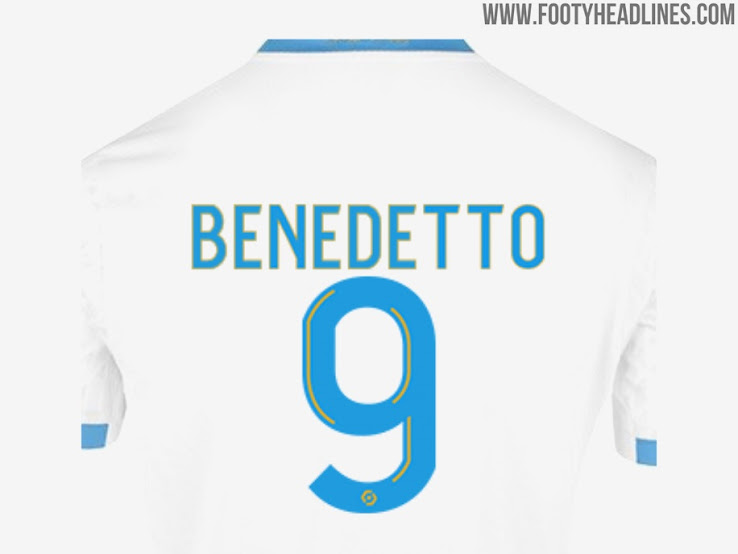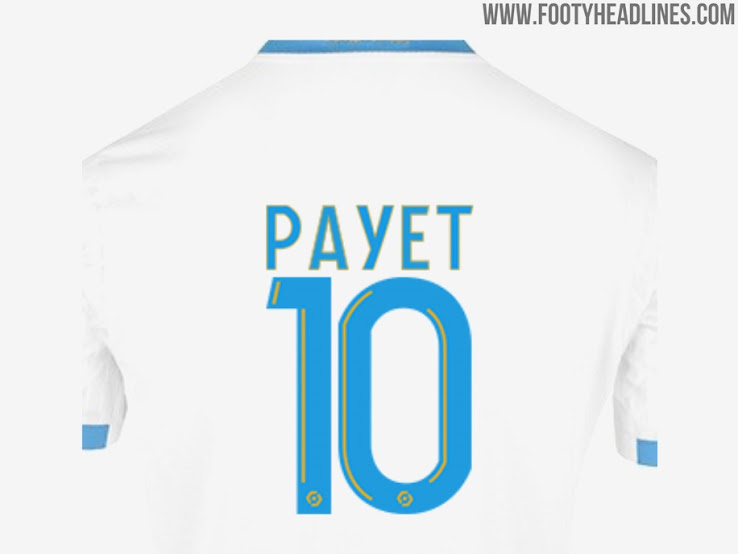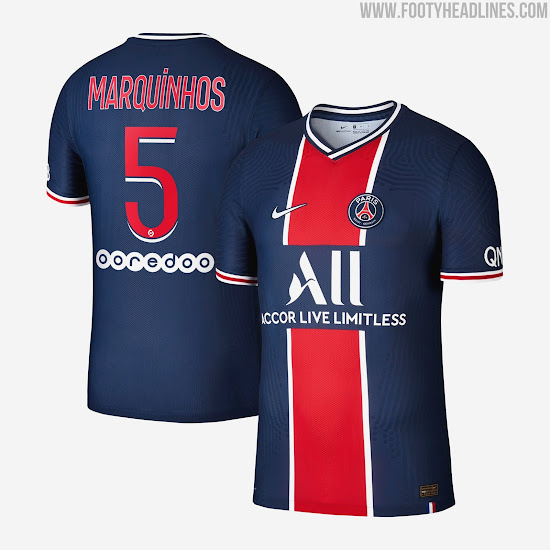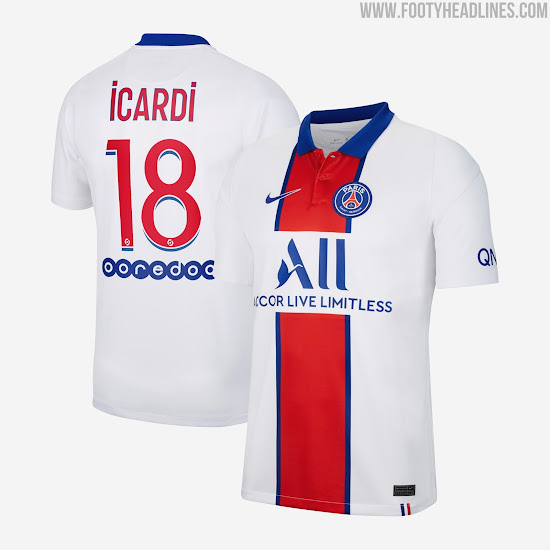
OFFIZIELL: Drei brandneue Ligue 1 20-21 Schriftarten veröffentlicht
Update: Mit der Veröffentlichung der Nike Paris Saint-Germain 2020-2021 Heim- und Auswärtstrikots erhalten wir einen Blick auf die Schriftart, die PSG in der Saison 2020/21 verwenden wird. Paris SG entschied sich für jene Schrift, die einen 3D-Effekt erzeugt.
Die Ligue 1 bestätigte den bisherigen Leak sowie die Designs, die bei Olympique Marseilles Trikot-Launch enthüllt wurden, und enthüllte gestern die gesamte Palette der Nummerierung, die ab der Saison 2020-21 verwendet werden soll.
Die neue Ligue 1 Schriftart ersetzt den bisherigen, 2008 eingeführten Stil und soll einen moderneren Look bieten und gleichzeitig mit der überarbeiteten visuellen Identität der Liga übereinstimmen.
Ab dem Beginn der Saison 20-21 haben die Teams der drei französischen Top-Divisionen (Ligue 1, Ligue 2 und Championnat National) die Wahl zwischen drei verschiedenen, von der Liga entworfenen Schriftarten. Nun erhalten wir einen ersten Blick auf eine der drei neuen Ligue 1 2020-21 Schriftarten.
Ligue 1 2020 Trikot-Schriftart
Dieses Bild zeigt alle drei Stile, die die Mannschaften in der Saison 2020-2021 verwenden können.
Alle drei Schriftarten basieren auf den gleichen Zahlenformen, was moderner als der vorherige Stil ist und gleichzeitig eine willkommene Vielseitigkeit bietet.
Bei den Modifikationen, die an jedem der Designs vorgenommen wurden, handelt es sich um verschiedene Randstile - einen an der Außenseite, einen an der Innenseite der Formen und einen, der einen 3D-Effekt bietet.
Die Teams können den von ihnen gewünschten Stil frei wählen und sogar zwischen Heim-, Auswärts- und Ausweichtrikots wechseln.
Am unteren Ende der neuen Ligue 1 2020-2021 Schriftart befindet sich das neue Emblem der Liga.
Wir gehen davon aus, dass die Beschriftung des Spielernamens in allen Stilen der Ligue 1 20-21 Schriftart gleich sein wird. Die Liga hat bestätigt, dass die Verwendung einer Umrandung der Namen - anders als bisher - optional sein wird. Sollte sich eine Mannschaft für die Verwendung eines solchen Rahmens entscheiden, muss dieser eine andere Farbe als die Grundform der Buchstaben sowie eine andere Farbe als das Trikot haben.
Die Liga lieferte sogar detaillierte Gebrauchsanweisungen:
Auf den Trikots der Spieler müssen die Namen in einer Höhe von 6 cm verwendet werden. Bei langen Namen, wie dem von Lyons Reine-Adélaïde, ist es möglich, sie zu komprimieren, um die Breite des Trikots zu respektieren. Ebenso ist es bei kurzen Namen wie Glik möglich, den Buchstabenabstand zu vergrössern, um die Sichtbarkeit für TV-Bilder zu verbessern.
Nummern sollten eine Höhe von 20 cm haben. Auf der Hose der Spieler müssen die Zahlen 10 cm hoch sein.
Altes Design
Die Ligue 1 2020 Schriftart wird ab 2020-21 und wahrscheinlich mindestens einige Jahre lang verwendet werden.